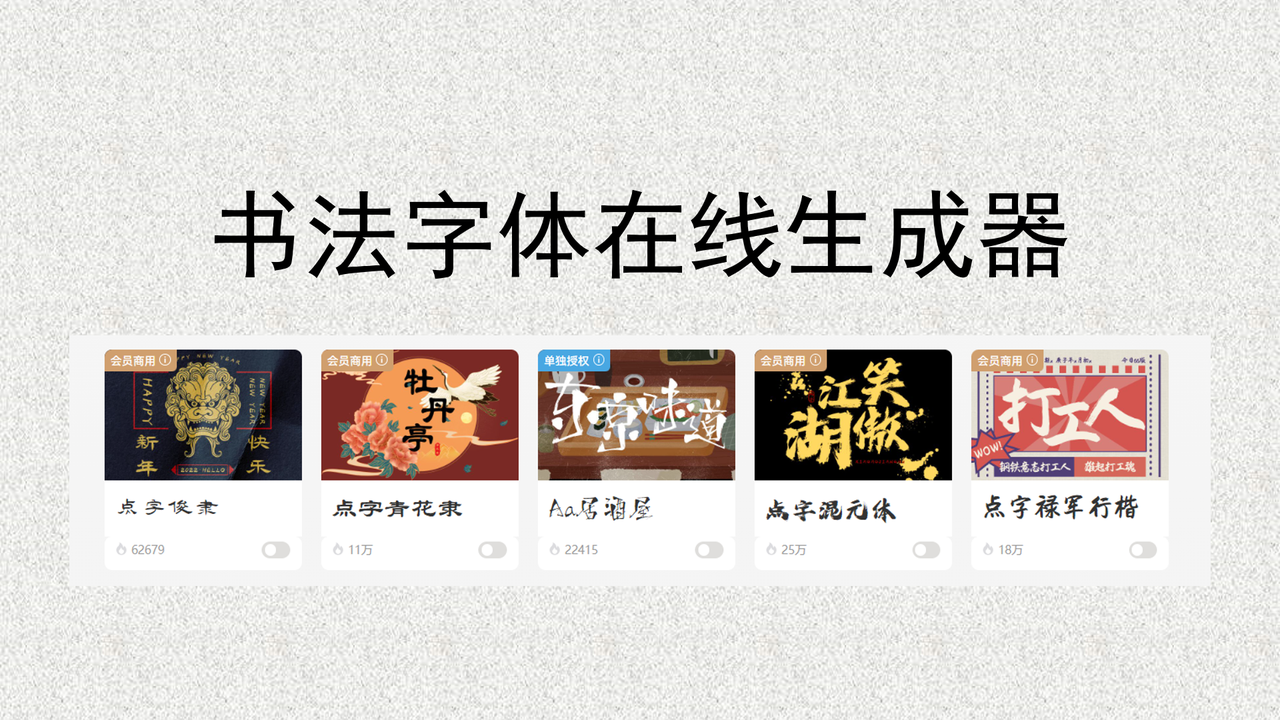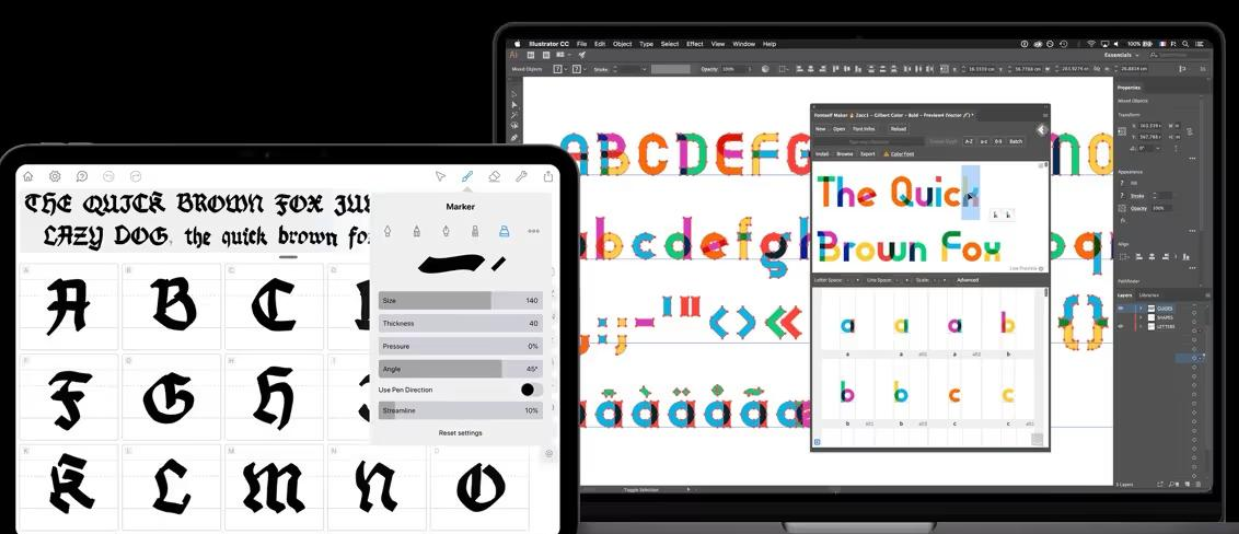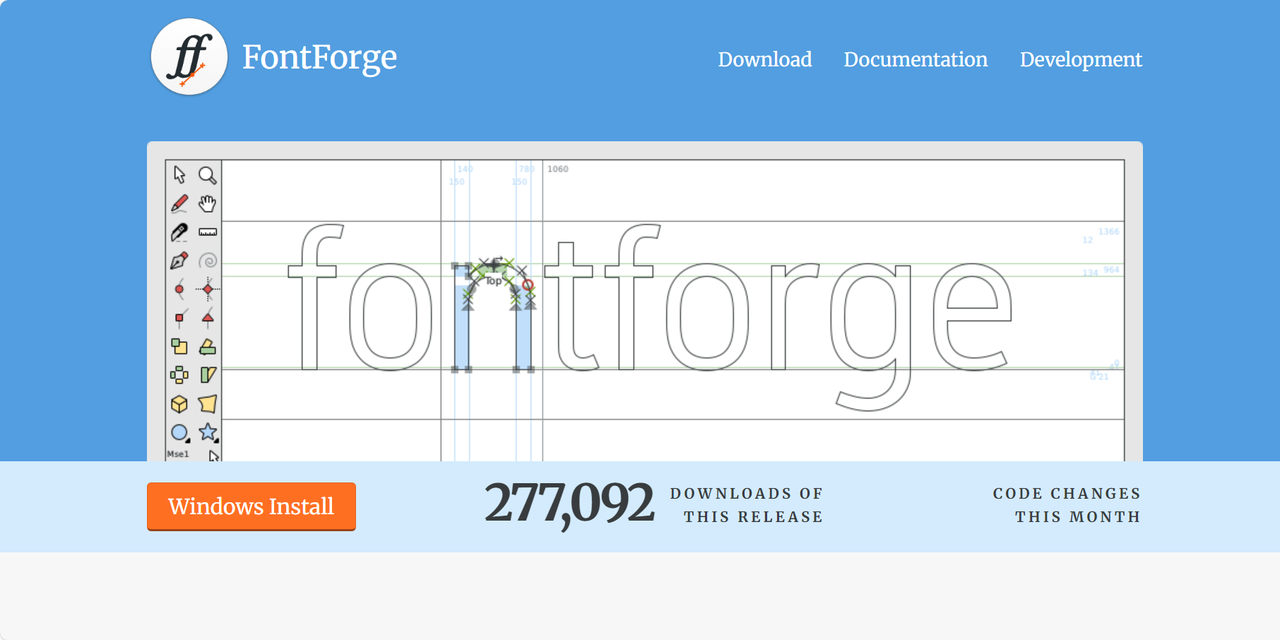
设计师必备的书法字体在线生成器,赶快收藏
书法字体往往能够传递出丰富的文化底蕴,同时还能让你的设计更富有精致感和高级感。优质且好用的正版书法字体授权费用很高,自己设计字体又门槛很高,时间成本和技术成本都是最大的问题。书法字体在线生成器的出现完美解决了这些困境,打开王哥即可一键生成各类书法字体,并且支持预览和高清下载,新手小白也能快速获得专业的书法体。本文为大家精选了 5 款风格迥异但功能强大的书法字体在线生成器,从 AI 深度融入的字体生成平台到无需安装的即开即用的字体神器,总有一款可以满足你的日常设计需求,跟着我一起来了解一下吧。
一、字由
近些年来,字由在国内设计师群体中相当流行,它改变了传统“下载——安装——使用”的选择字体方式,升级成为“在线预览——直接生成——一键保存”的高效字体管理流程。字由官网收录了海量正版的字体资源,更是覆盖了很多经典常用字库,例如汉仪字库、华康字型、点字库、优设字库、站酷字体等等,英文字体资源也是应有尽有哦。
关于在线生成书法字体,我要着重介绍字由的【AI 字体】功能,用户只需要输入目标文本内容,就可以一键生成同款书法字体,整个过程不超过 30s,便捷又高效。用户进入字由官网后,在上方菜单栏点击【字体工具】—【AI 字体】,成功进入生成字体页面;按照风格筛选“书法”字体,在一系列字体模板当中选择心仪的字体,单击字体“做同款”;输入自定义文本内容,点击“立即生成”,全程傻瓜式操作,无需掌握任何设计技巧和书法功底。需要提醒大家注意的是,为了保证书法字体生成的最佳效果,建议自定义文本内容和图片发字数保持一致哦。
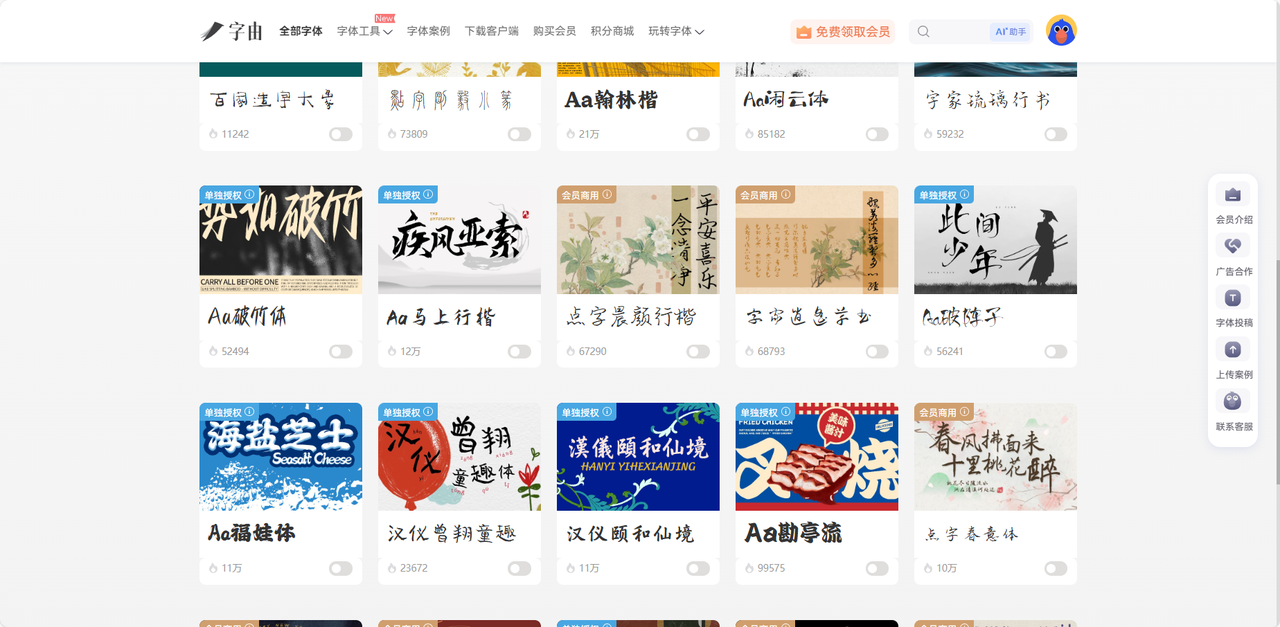
二、Fontself Maker
Fontself Maker 是一款可以将 Adobe Illustrator 和 Photoshop 直接升级为书法字体在线生成器的专业扩展工具,让每一个设计师都能快速做出一套属于自己的字体。不过这款工具的使用需要你掌握一定的设计能力,具体来说就是,用户在原本的 AI。或 PS 软件中,使用画笔工具、钢笔工具等绘制出自己想要的字母或图形,绘制完成后将该图层拖拽到 Fontself Maker 中,它会自动识别制作整套字体并将字体打包。除此之外,这款工具还支持创作带颜色和特效的彩色字体,提升字体的视觉吸引力。最值得夸赞的一点是,Fontself Maker 有交替字形和连字设计的功能,可以让整套字体更接近真实手写的呼吸感与自然感。它还提供很多细节性的功能,比如智能字距调整,用户能够一键完成全文字符的间距平衡,无需设计师手动校准每个字符的位置,能让你的工作效率大幅提升。
三、FontForge
FontForge 是一款完全免费且开源的书法字体在线生成器,是很多新手设计师或设计专业学生党的常用工具之一。它最大的魅力就在于零成本使用,且功能依旧保持专业性和实用性。对于想要从零开始打造一套书法字体的设计师来说,FontForge 是一个很好的选择,它提供了一个类似矢量绘图软件的编辑界面,用户可以直接在这里绘制每个字符的轮廓,精准控制笔画粗细、衬线形态、连笔程度等等,打造一套满足你所有需求的书法字体。如果你懂编程,FontForge 也为你提供了施展平台,允许用户编写自动化脚本,输入编码实现批量字形生成、格式转换等任务,提升大型字体项目的生成效率。
四、Calligraphr
Calligraphr 可以将真实笔墨转换为屏幕内呈现出来的电子形式,是一款与众不同的书法字体生成器。用户只需要进入 Calligraphr 官网下载预设的字符模板,然后将模板打印在普通的白纸上,用黑色签字笔或毛笔逐一手写对应的字符,最后将纸稿拍摄成图片,上传至官网,系统就会自动识别每个手写字体并转换为可以设计修改的矢量字符,最终可以一键导出为能用于各大设计软件中的专业字体文件格式。这样生成出来的字体完美保留了手写书法中的笔墨韵味,最关键的是,Calligraphr 还提供了字符随机化功能,可以为同一个字符设置多个手写变体,在排版时随机调用,让最终的文字效果更像是真实手写的自然差异。
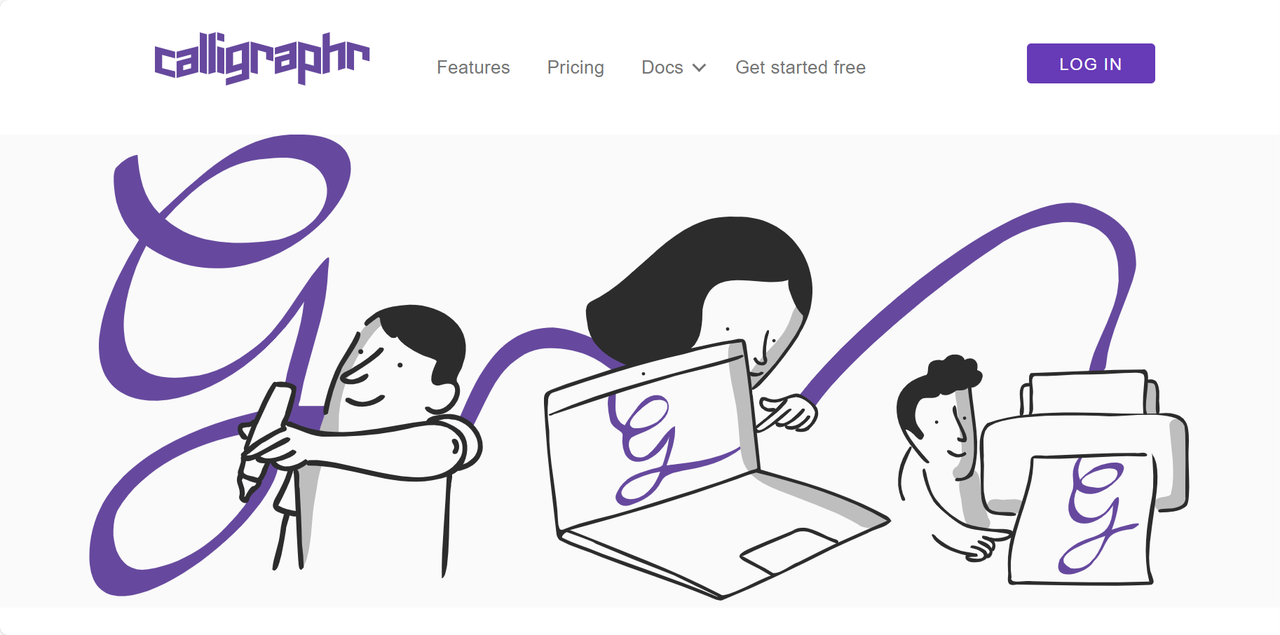
五、FontArk
与其他字体生成器不同,FontArk 是基于字形骨架进行字体生成,用户需要先设置好每个字符的核心结构,系统会根据字形骨架自动生成完整的书法字体轮廓。它提供了路径编辑、自由变形、覆盖图层等高级矢量编辑功能,也支持同时编辑多个字符。FontArk 的亮点功能我就是轮廓生成器,具体来讲就是在原始的字形骨架周围生成完整的轮廓,当你需要修改字形的时候,只需要调整骨架节点的位置,还可以通过调整参数来改变字体粗细或圆润程度,这样整个字符轮廓形态都会智能联动变化,呈现出来的字体效果自然且随性。